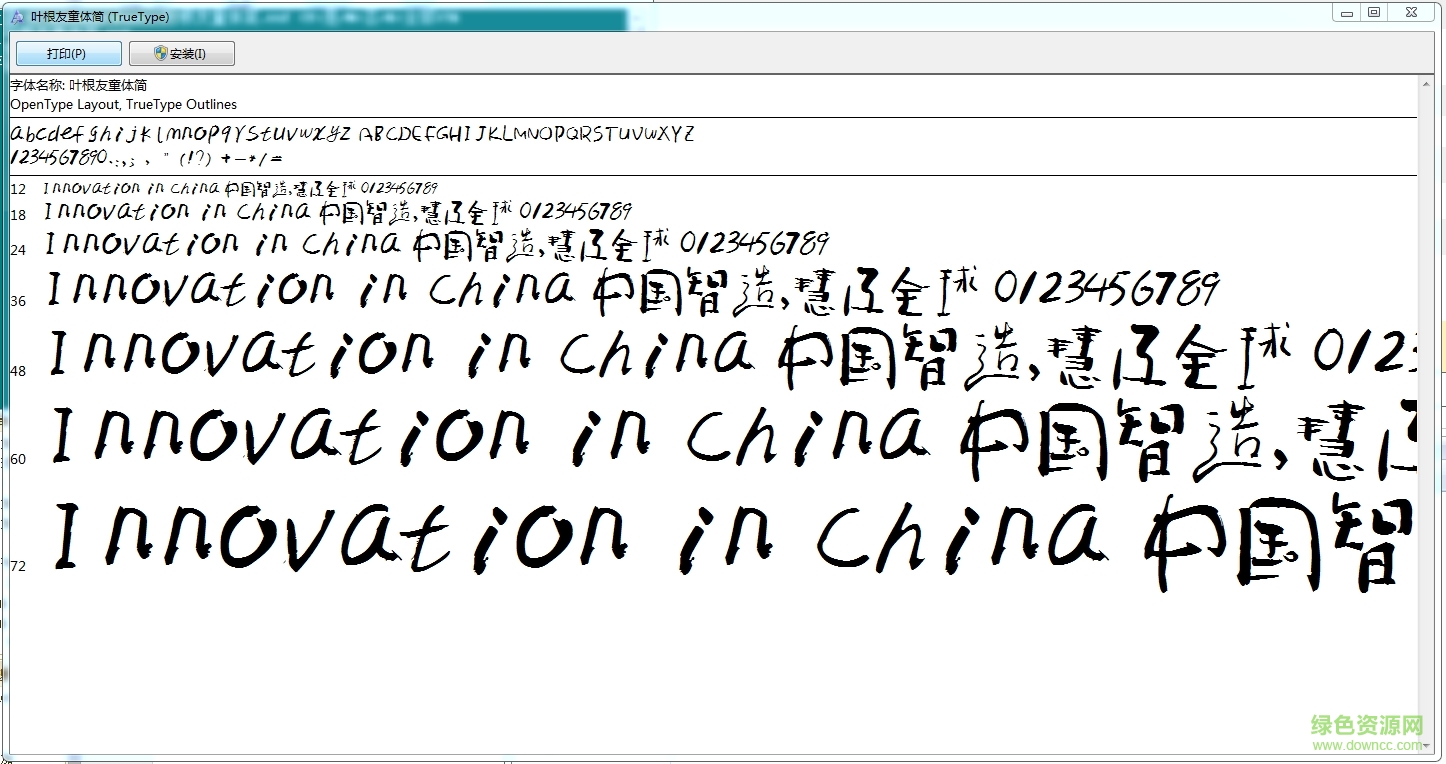
葉根友童體簡(jiǎn)是葉根友先生創(chuàng)作的一款兒童設(shè)計(jì)方面的簡(jiǎn)體兒童字體,該字體充滿了童趣,字形飄逸效果出眾,可應(yīng)用于繪畫設(shè)計(jì)、藝術(shù)創(chuàng)作、平面廣告、印刷包裝、兒童繪畫等領(lǐng)域,喜歡的小伙伴快來綠色資源網(wǎng)下載吧!